Monotypeが人気書体「筑紫書体シリーズ」や「Helvetica Now」などを組み合わせた和欧混植フォント6ファミリーをMonotype Fontsからリリース
Monotype Imaging Inc.の日本法人Monotype株式会社は、MonotypⓇクリエイティブ・タイプディレクター小林章氏、書体デザインディレクター藤田重信氏が監修し、日本とグローバルのチームが共同で制作した「和欧混植フォント」6ファミリーを、世界最大級のフォントライブラリを持つフォントサービス「Monotype Fonts」からリリースした。
Monotypeが提案する、美しく心地よい和欧混植フォント
和欧混植とは、日本語の文字(和文書体)とアルファベットなどのラテン文字と数字(欧文書体)を組み合わせた文字組版のこと。デザインやレイアウト上の調整を行い、違和感なく両方の文字体系を組み合わせることで、より美しく読み心地のよい文字の表現が可能になった。
Monotypeを代表する和文・欧文書体である、筑紫Ⓡゴシック、筑紫R明朝、フォントワークス UDⓇ角ゴ_ラージ、ニューロダン™ 、Gill SansⓇ Nova、HelveticaⓇ Now Display、PalatinoⓇ Nova、DINⓇ Next、SyntaxⓇ Next、SabonⓇ Nextを組み合わせた。
本書体は、Monotypeと筑紫書体シリーズなどで知られるFontworksⓇがひとつになったことをきっかけに、よりフォントの持つ可能性を広げることを目指して誕生した新しいコンセプトのフォント。欧文と和文のデザインを一体化させたことで、文化や言語の枠を越えた自然な調和を実現している。このフォントは、デザイン性だけでなく、ユーザーの創造性を最大限に引き出すために柔軟に対応できる強固な基盤を提供。
和欧混植フォント一覧
筑紫明朝+Palatino Nova 7ウェイト
筑紫明朝+Sabon Next 7ウェイト
筑紫ゴシック+Gill Sans Nova 8ウェイト
筑紫ゴシック+Syntax Next 8ウェイト
ニューロダン+DIN Next 6ウェイト
フォントワークスUD角ゴラージ+Helvetica Now Display 8ウェイト
Monotype和欧混植フォントの特長
・厳選した書体の組み合わせと、混植時の美しさ
Monotypeの和欧混植フォントは、数ある和文・欧文書体から組み合わせを厳選。それぞれの持つ個性や美しさを活かし、可読性が高く洗練された印象を実現。
また混植時の見え方の美しさにもこだわった。洗練された欧文書体が和文中に入ることで、全体が引き締まる。特に数字は使用頻度が高いため、本書体を使用することで読みやすさや美しさがより際立つ。
多様化するコミュニケーションのニーズやグローバルな視点でのフォント活用が求められる中、和欧混植フォントは多様な場面での使用を可能にし、コミュニケーションをより豊かで魅力的なものにするために開発された。
・特別なソフトや知識は不要
和文と欧文の混植は、デザインツールのレイアウト機能を利用し、専門知識も必要だったたが和欧混植フォントを利用することにより、特別なソフトや知識がなくても、誰にでも手軽に美しい文字表現が可能になった。
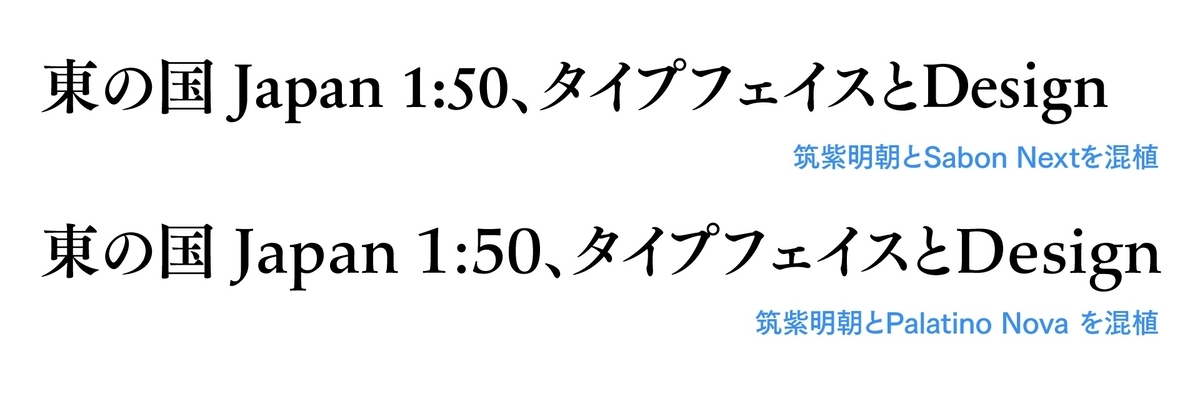
筑紫明朝に対して、2種の混植組み合わせを用意
提供を開始する6書体
Monotypeを代表する和文・欧文書体から、6つの組み合わせが生まれた。組み合わせごとに複数のウェイトとイタリック*も用意している。
*イタリック体をAdobe Illustratorなど主要デザインツールで使用する場合、Open Type機能の「イタリック」を選択して利用。
筑紫明朝+Palatino Nova(7ウェイト)
活字・写植時代の本質を踏襲し、明朝体とはどうあるべきかを最大限に考慮した筑紫明朝と、書籍の本文・見出しを問わず、そして時代に左右されず使われ続けているセリフ書体Palatinoの改刻・ウェイト拡張版Palatino Novaを組み合わせた。
柔らかさや伝統を感じる混植で、長文で使用しても読みやすく、印象に残る言葉を大きく表示することにも適している。
筑紫明朝+Sabon Next(7ウェイト)
活字・写植時代の本質を踏襲し、明朝体とはどうあるべきかを最大限に考慮した本文用書体 筑紫明朝と、書籍の本文、見出しを問わず、しかも時代に左右されず使われ続けているセリフ書体Sabonの改刻・ウェイト拡張版Sabon Nextを組み合わせた。
伝統的でエレガントな印象を生み出す組み合わせで、品格や華やかさを感じさせたい場面に適している。
筑紫ゴシック+Gill Sans Nova(8ウェイト)
現代のシャープさやクリーンな硬質さと、クラシックな味わいや柔らかな部分を融合させた筑紫ゴシックと、伝統や格調を演出したい場合に使われるヒューマニスト・サンセリフ体の先駆的書体Gill Sansの改刻・ウェイト拡張版Gill Sans Novaを組み合わせた。
可読性に優れ、信頼感や伝統の中にも柔らかい印象を感じさせたい場面に適している。
筑紫ゴシック+Syntax Next(8ウェイト)
現代のシャープさやクリーンな硬質さと、クラシックな味わいや柔らかな部分を融合させた筑紫ゴシックと、ヒューマニスト・サンセリフ体ではFrutigerⓇと並んで評価される書体Syntaxの改刻・ウェイト拡張版Syntax Nextを組み合わせた。
明るさと読みやすさの中に、現代的で洗練された印象のある混植です。本文からデジタルデバイスまで幅広く活用できる。
ニューロダン+DIN Next(6ウェイト)
フォントワークスのゴシック体ニューロダンとドイツの工業用規格から生まれたDIN 1451をベースに、現代的なサンセリフ書体DIN Nextを組み合わせた。
機能的でシンプルな印象のある混植で、小さい文字でも読みやすく機能的。
フォントワークス UD角ゴ_ラージ+Helvetica Now Display(8ウェイト)
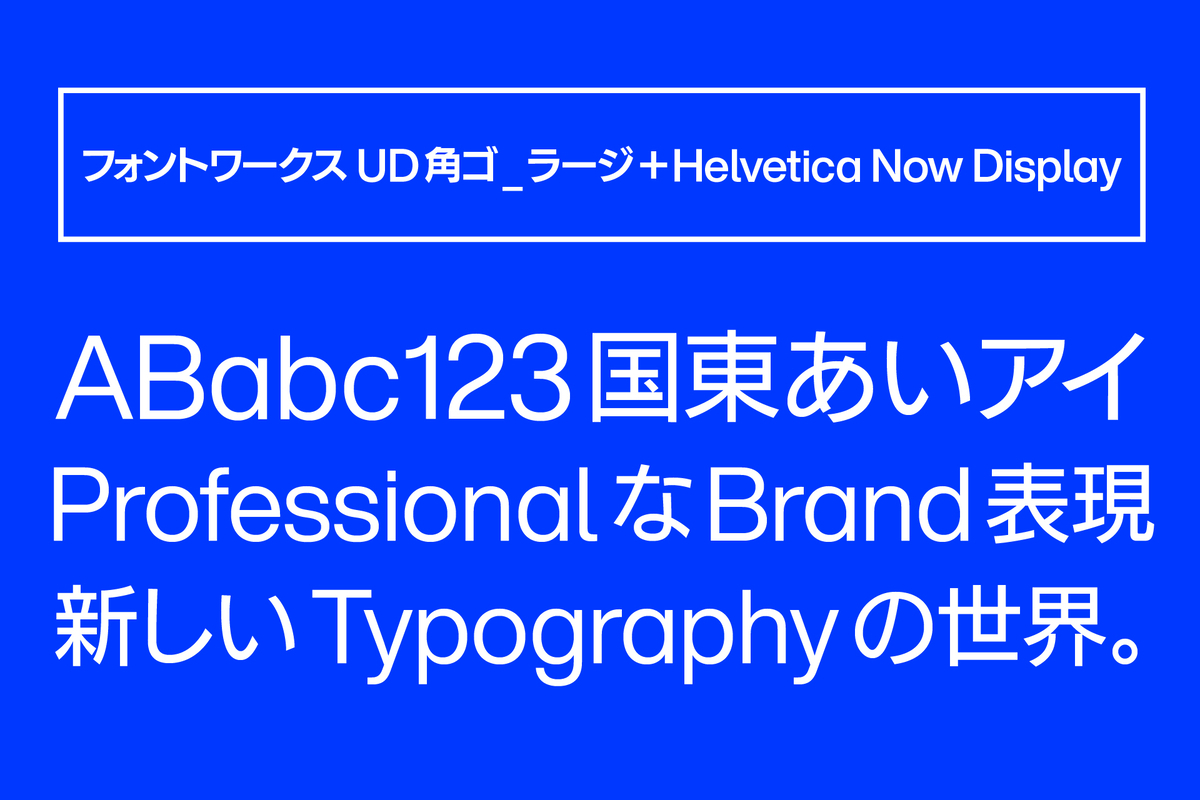
見出しに最適なモダンゴシック体 ニューロダンをベースにしたフォントワークス UD角ゴ_ラージと、現代のブランディングの課題を解決する書体として誕生したHelvetica Nowのうち、大きな見出し用に字間が調整されているDisplayを組み合わせた。
明瞭で伝わりやすい組み合わせで、サインや見出し、機能説明などに適している。
MonotypeとFontworksが協力して、両社の強みを最大限に活かした混植フォントを全世界に向けて発表します。 情報の多言語化の時代の要求に応えるため、Fontworksの和文書体にサイズや位置を合わせた欧文書体を組み込みました。 日本語と西欧の言語を混植する際に、これまでの和文従属欧文とは違った世界レベルの品質を提供できることを嬉しく思います。
写植時代以後、和文を作るデザイナーの多くは付属の英数字をデザインする際、CenturyやHelvetica等オリジナルを使うことはできず、それらに似たイメージでデザインする必要がありました。
MonotypeとFontworksが1つになったことで、これら欧文が和文字用に調整と組み合わせが可能になりました。 「真の和文フォント」として、世界に発信できるものになるでしょう。